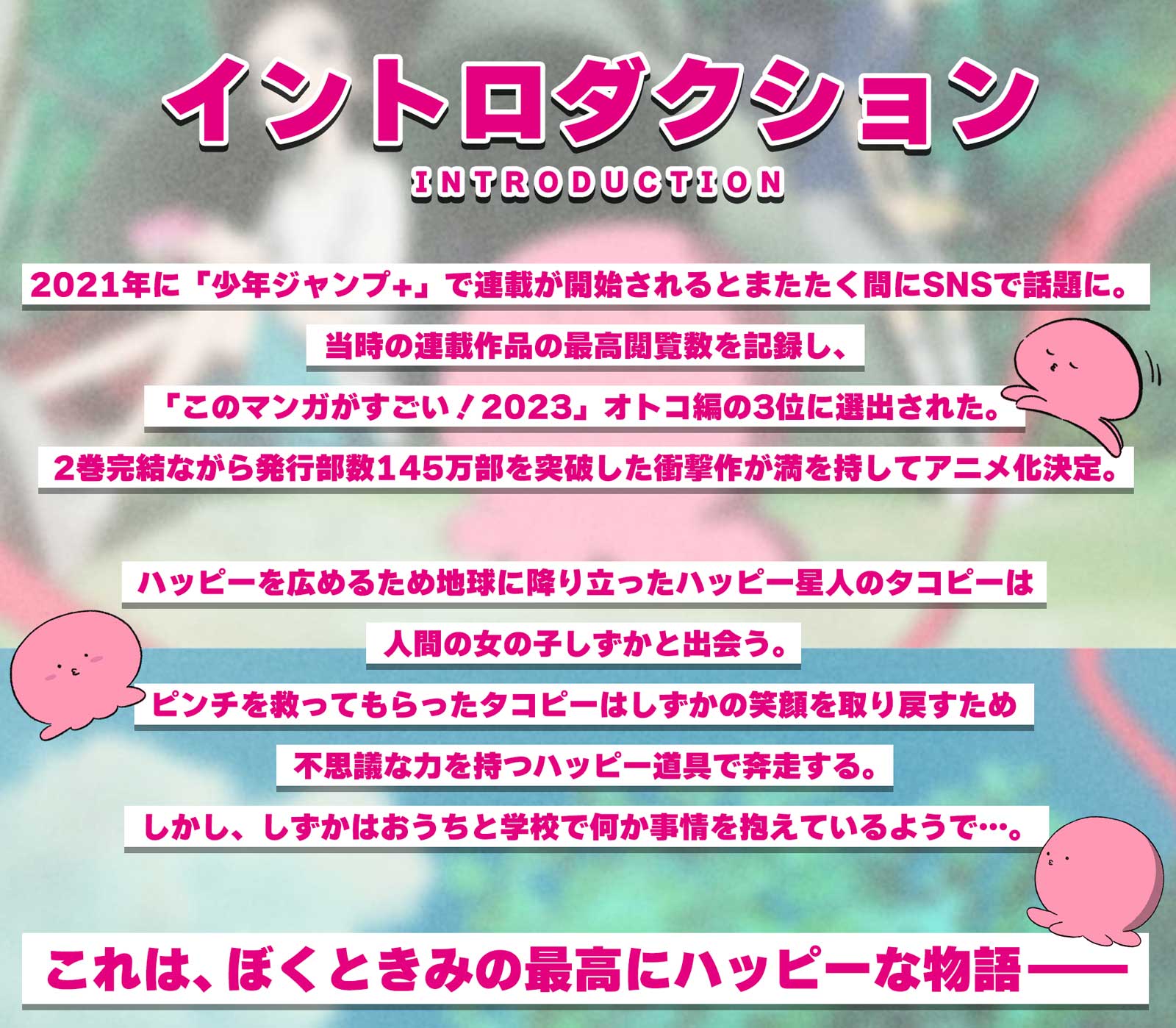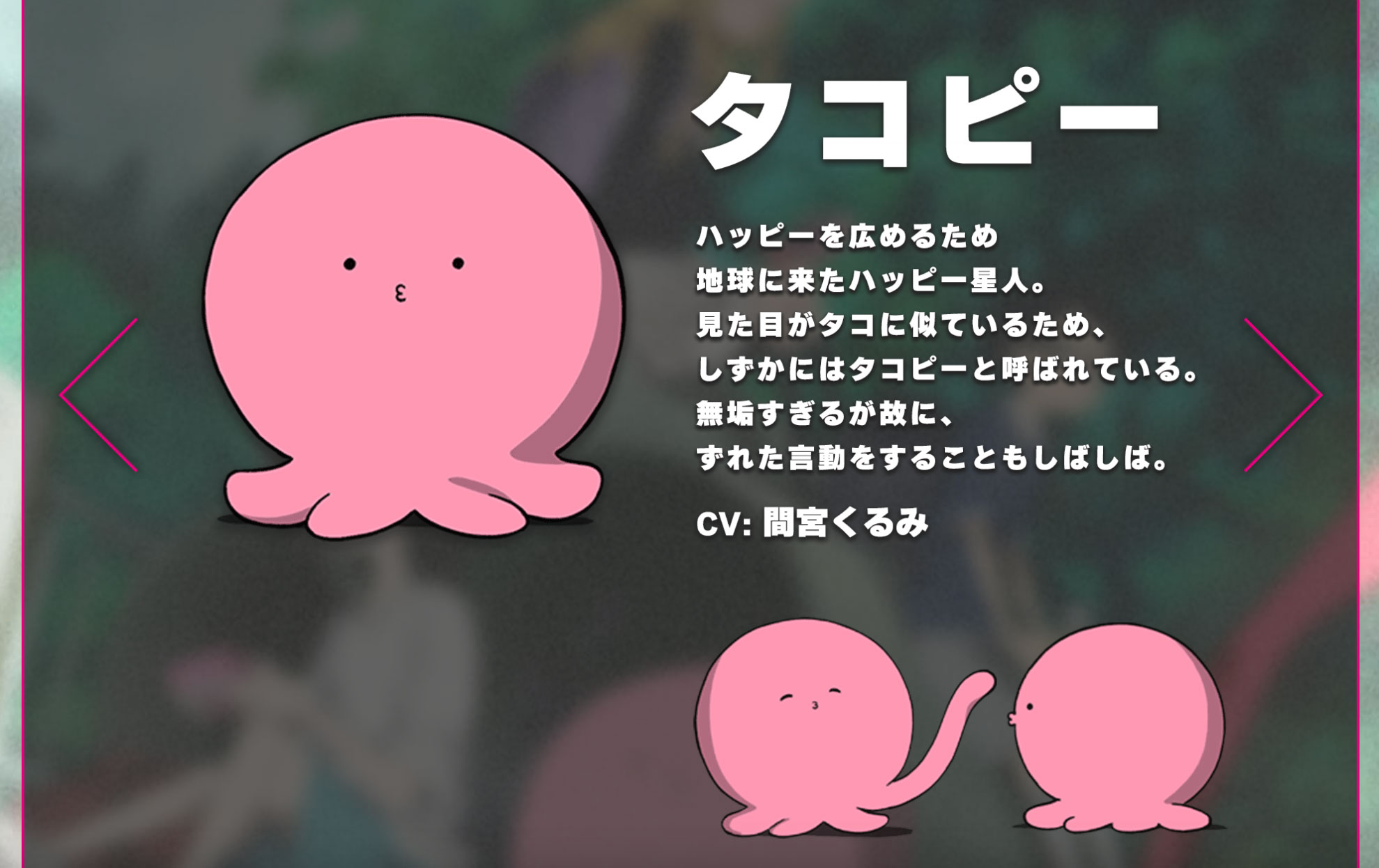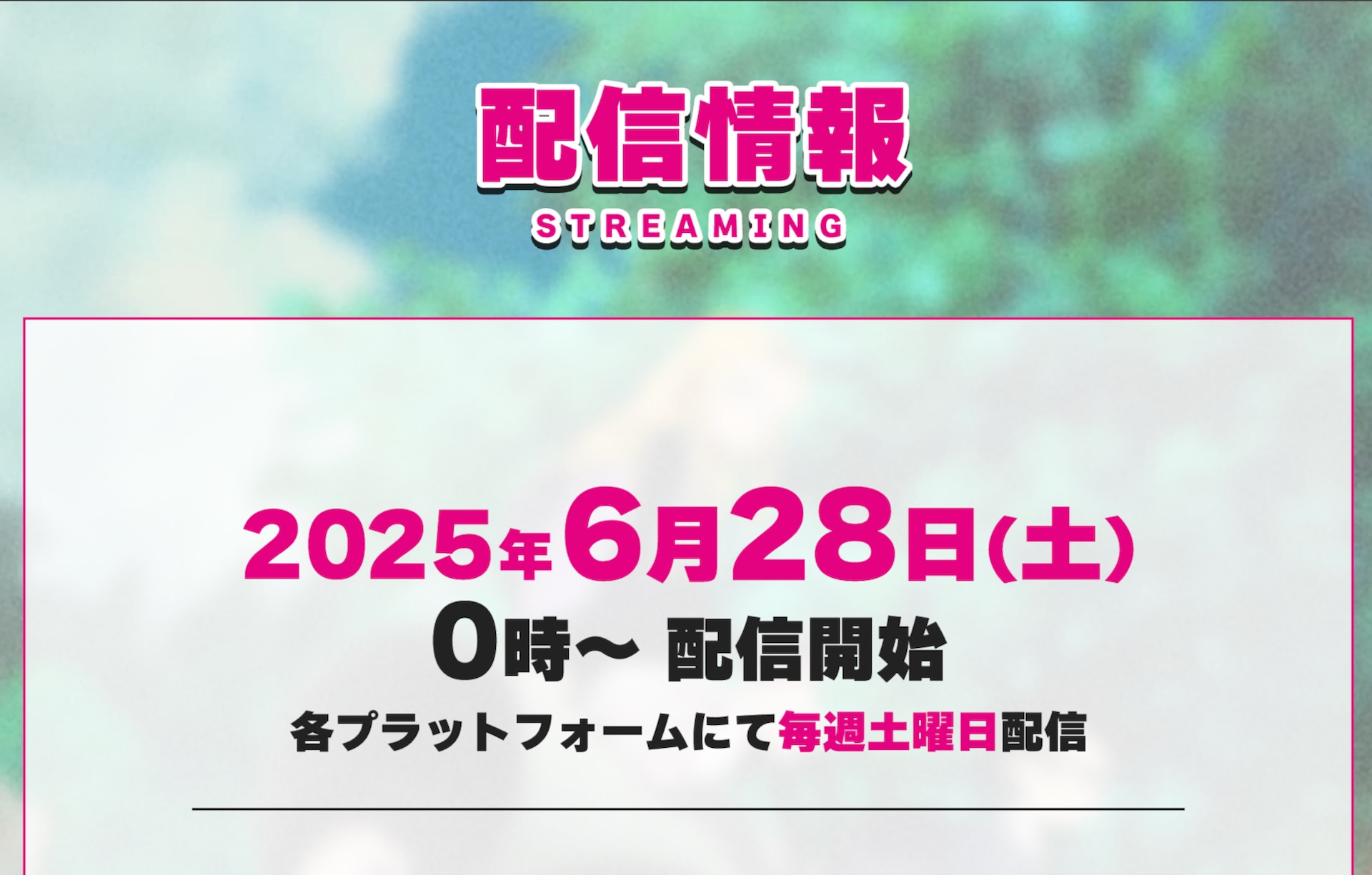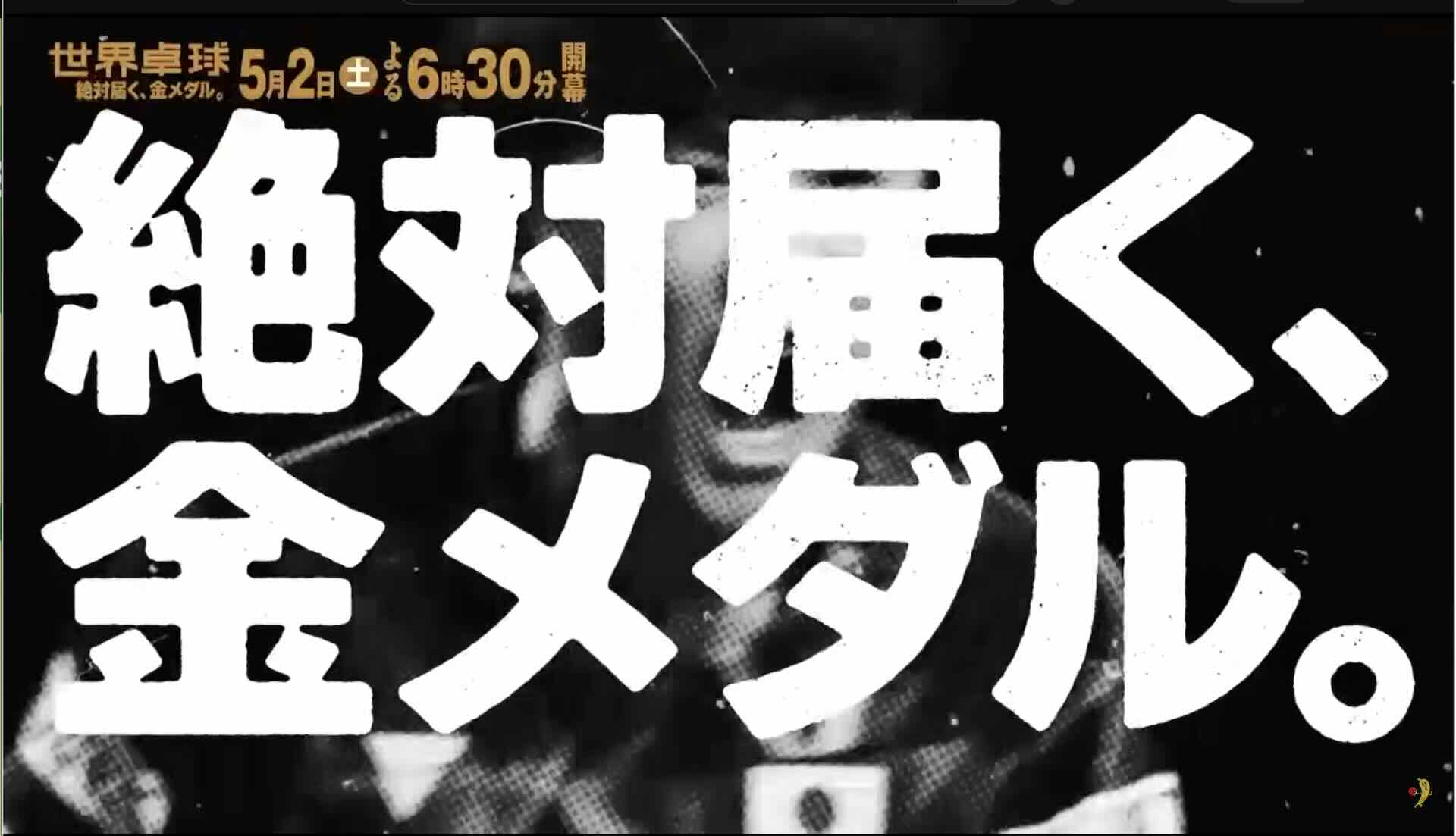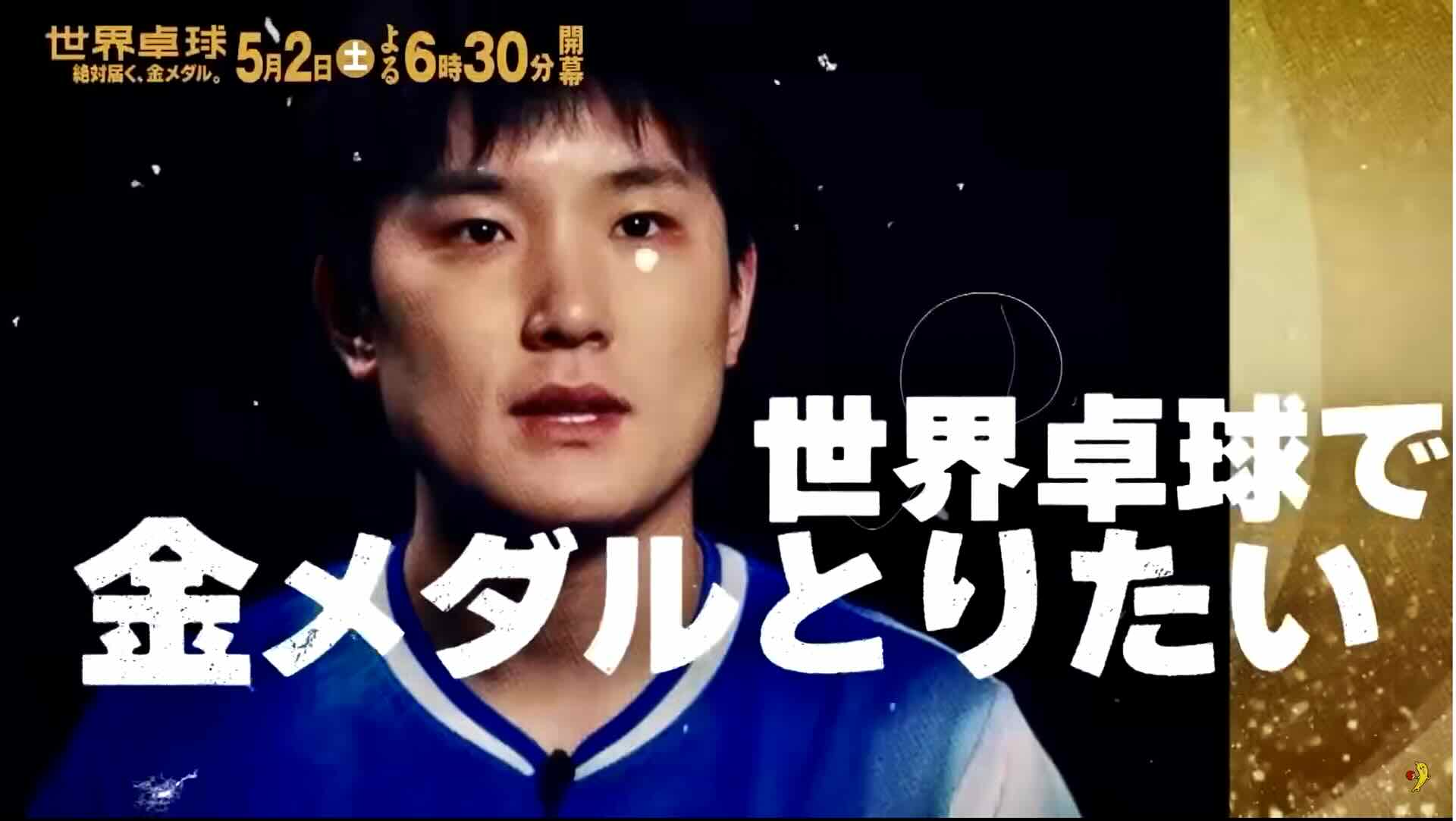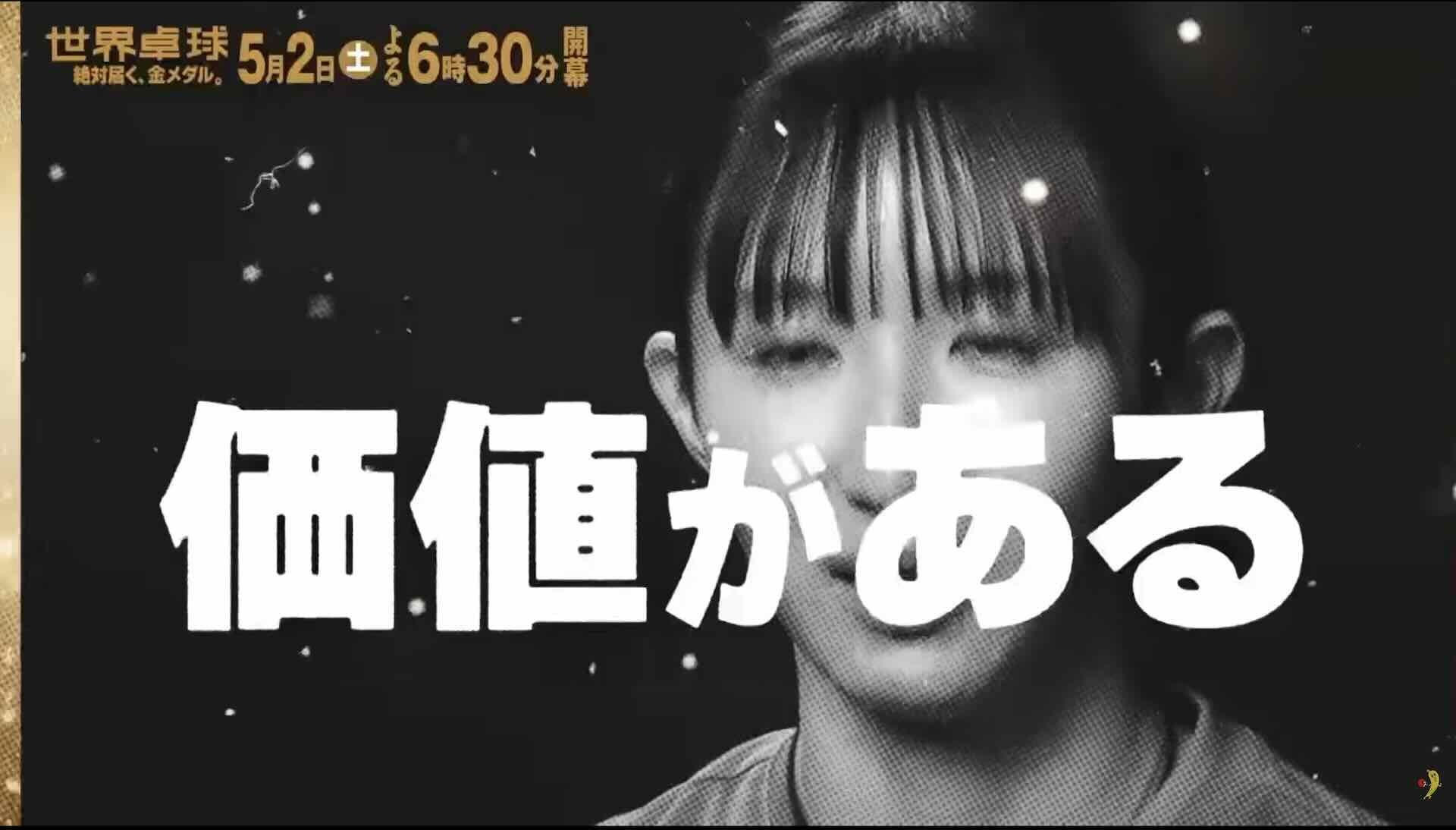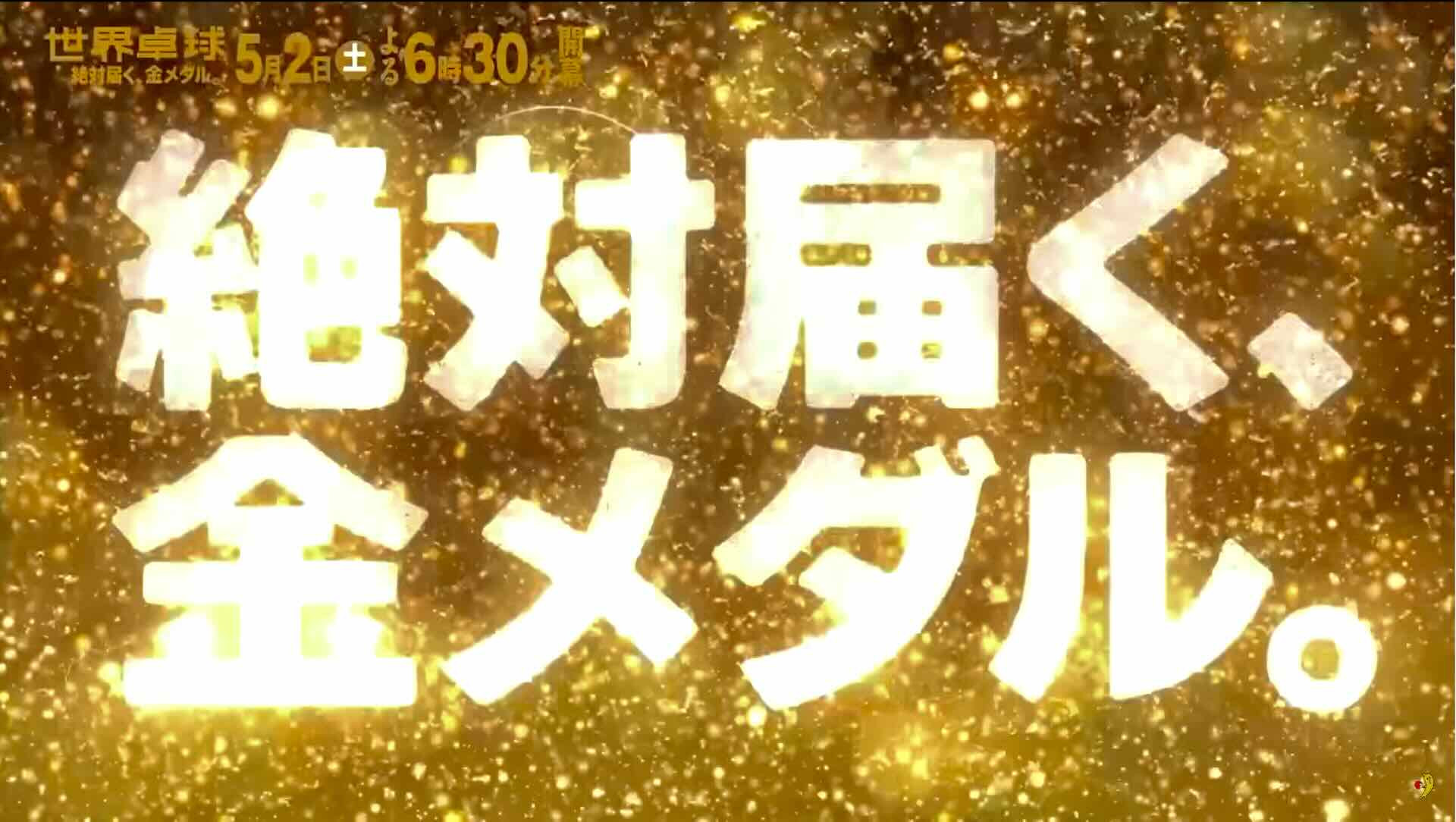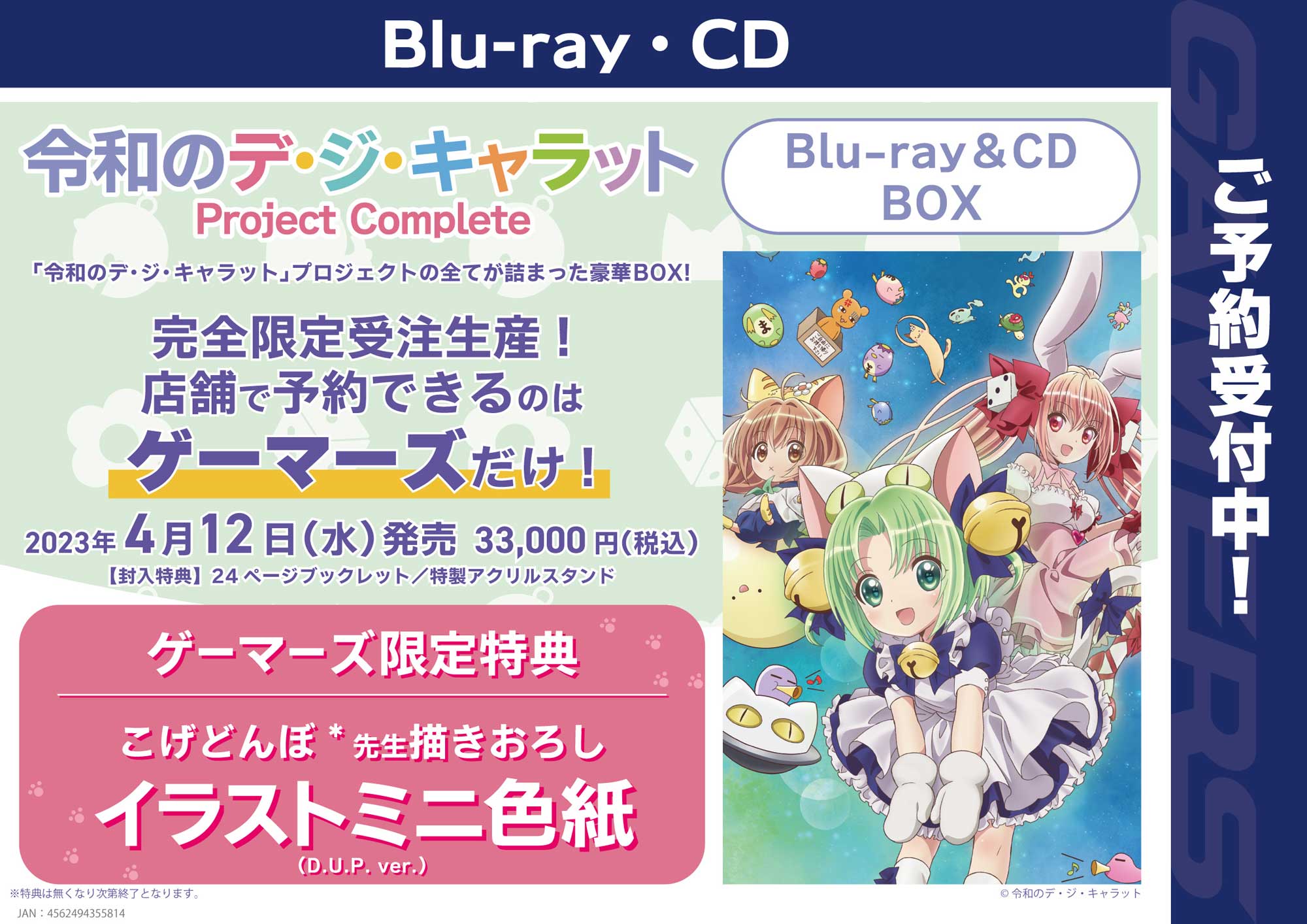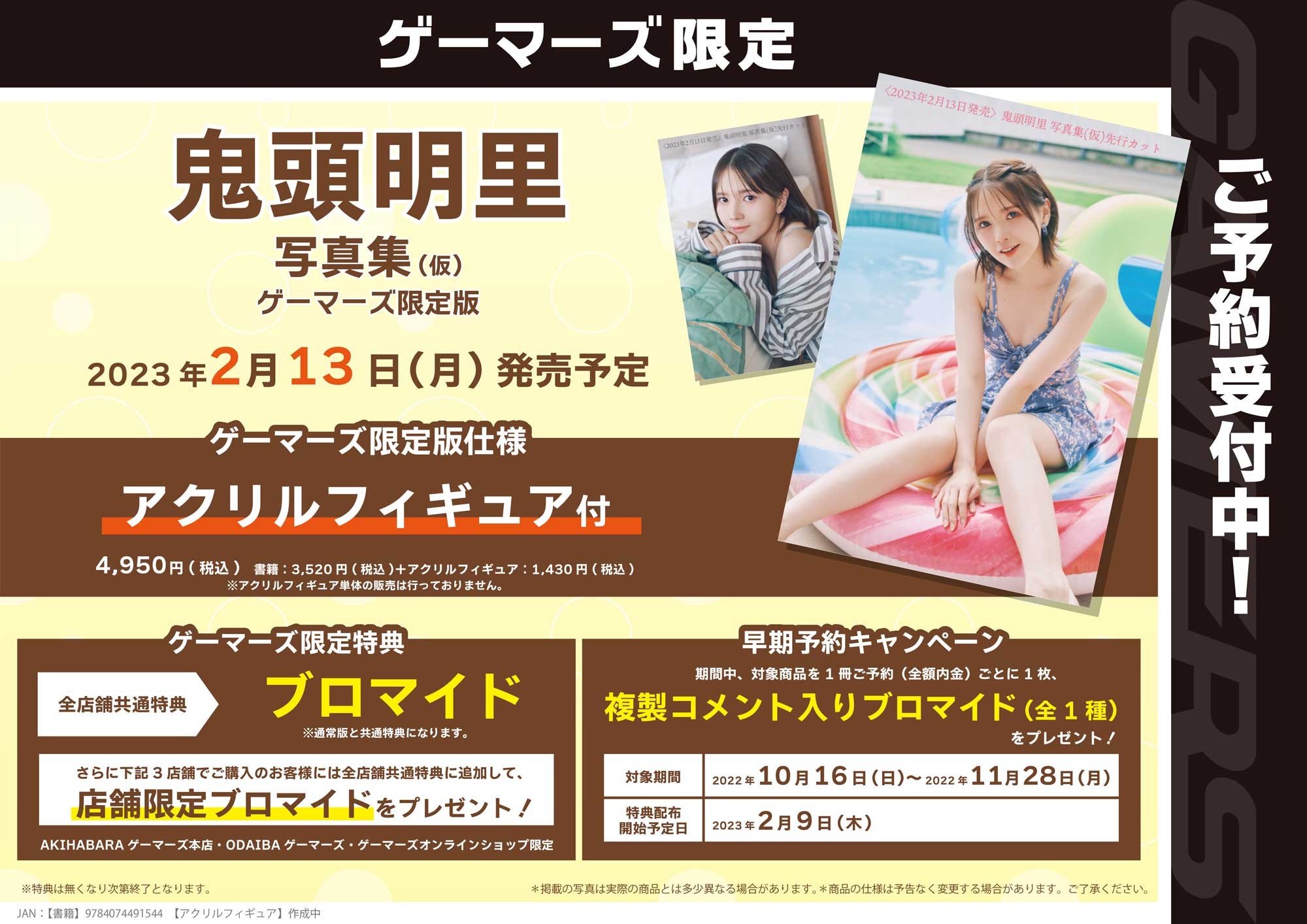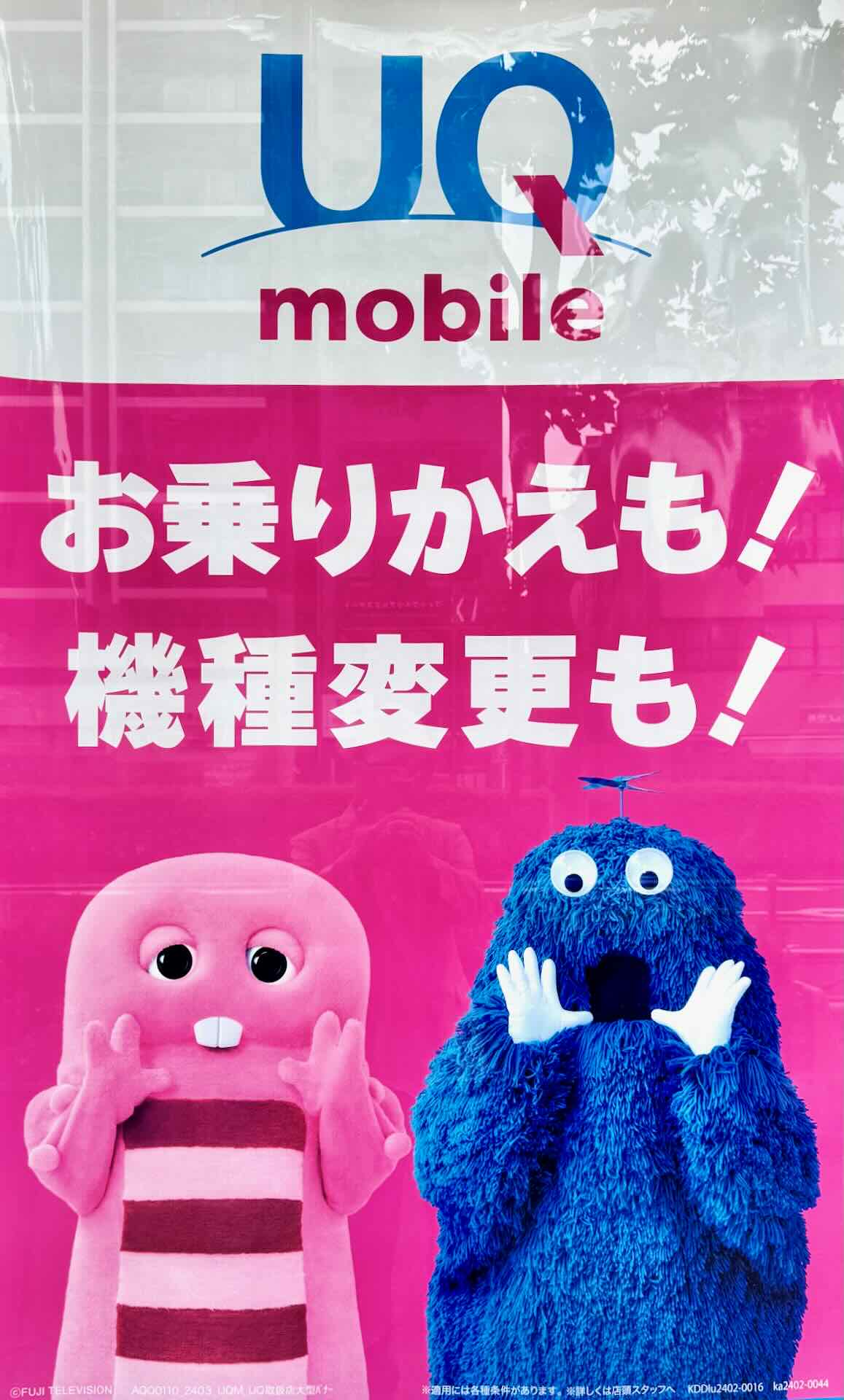
クノールの贅沢野菜スープ。
これも。
まだある。
もう1枚。
よみうりランドの広告。
大阪都構想に関する法定協議会。
よみうりランドのプール。
「プールWAI」が、ルイカ書体(英字のIの形で判る)。
その上下の小さな文字は「わんぱくルイカ」書体。
書名:飛び出す!海のいきもの大図鑑
これは、ポスターかな?
ディスカウントストア「ドンキ」のCM。
これも。
もうひとつ。
携帯電話会社のポスター。
ショーウインドウの中に貼られていたものを、ガラス越しに撮った…。
世界卓球2026ロンドン100周年大会 (団体戦)5月2日(土)開幕!
これも。
もうひとつ。
金色のバージョンも。
この動画の中では、ルイカは紹介されていない…残念!
映画館で見かけたやつ。
ルイカ書体は、クセのない普通の表情でありながら、強く訴える力も持っている…。